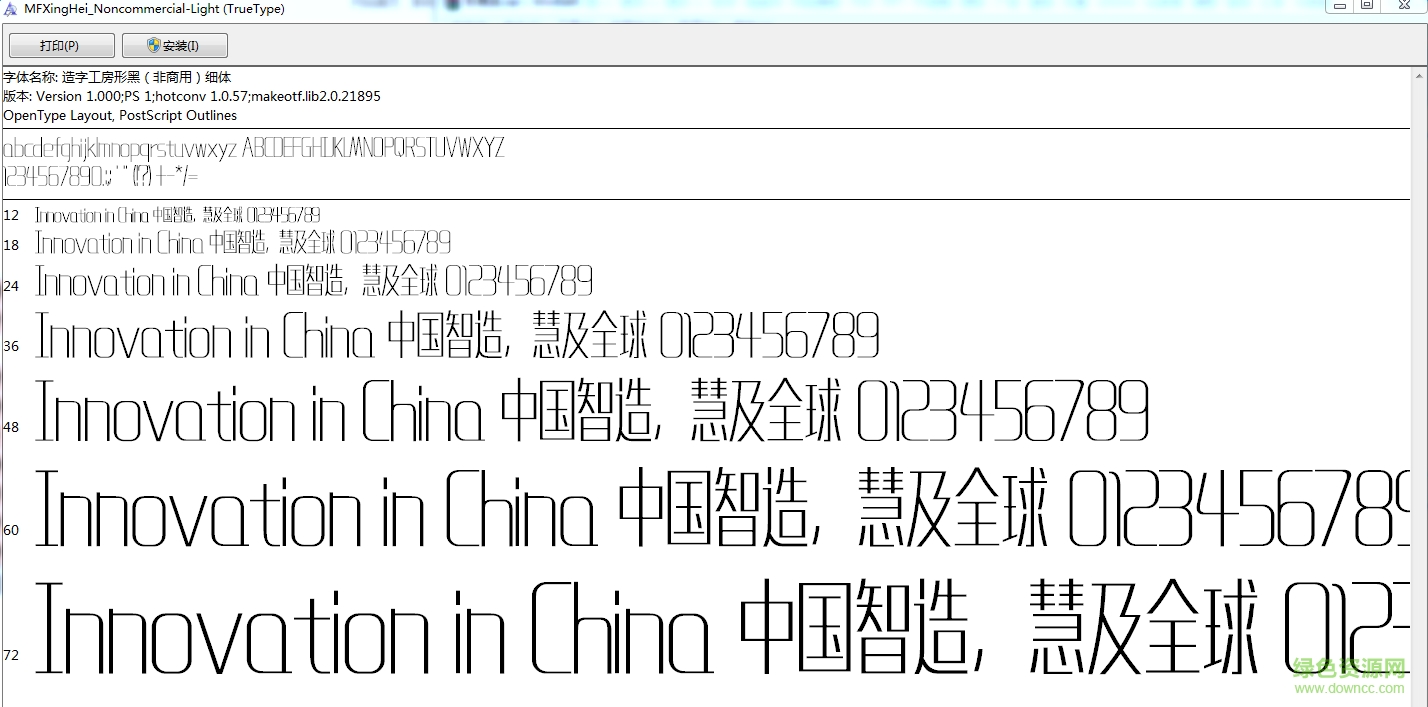
造字工房形黑體是一款造字工房類柔美風(fēng)格字體軟件,形黑體給人非常正式的感覺,適用于品牌形象的推廣,也深受廣大書法家的喜愛,還有更多好看字體盡情期待,歡迎到綠色資源網(wǎng)下載體驗(yàn)!
造字工房形黑體字形筆畫簡(jiǎn)約、平直,柔美的弧線讓整體字形更顯干練!精細(xì)的筆畫間凸顯匠師精雕細(xì)琢之力,柔中兼剛不失韌勁,是一款獨(dú)具特色的字體產(chǎn)品!極其適用于科技產(chǎn)品的品牌形象擴(kuò)展。